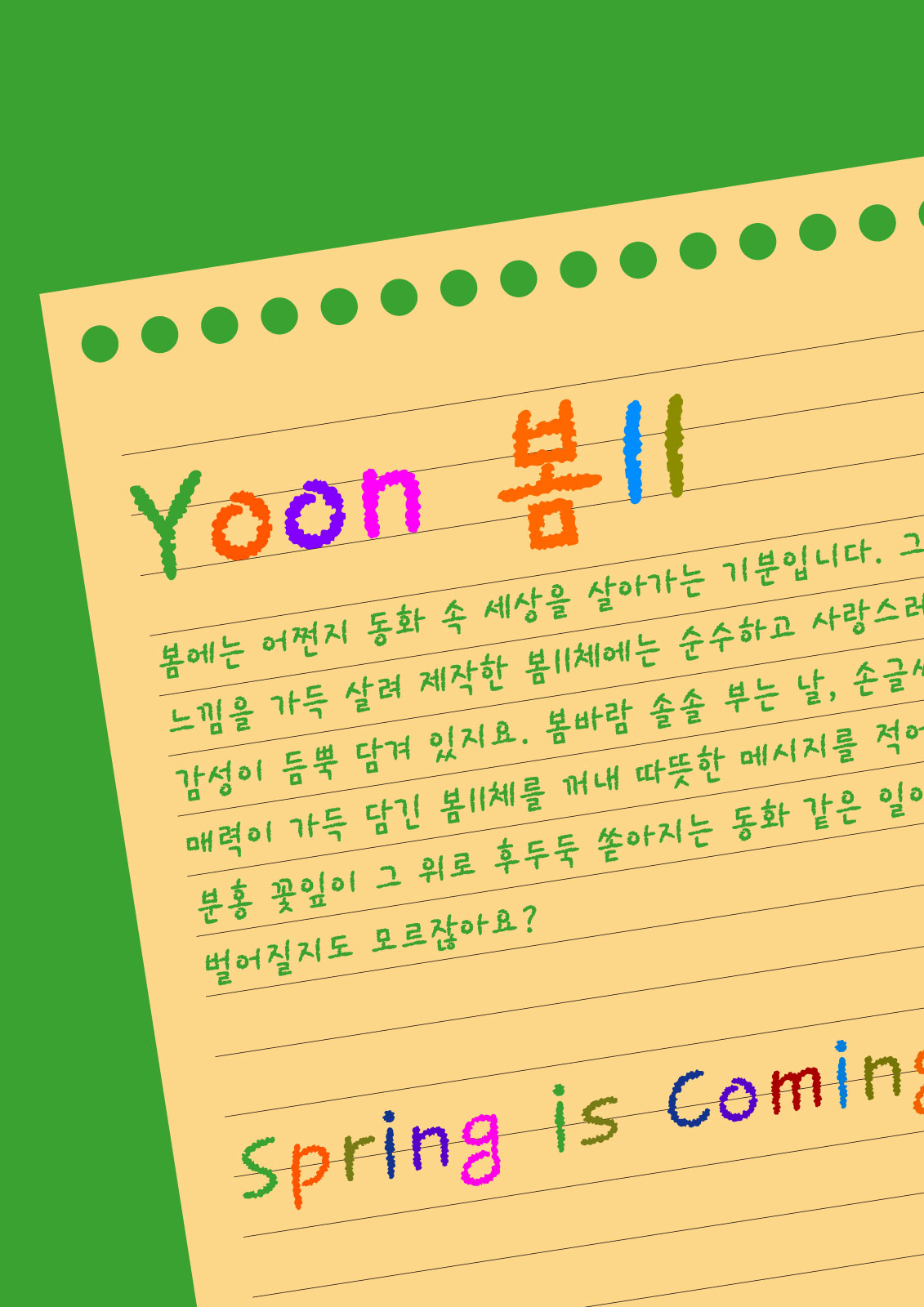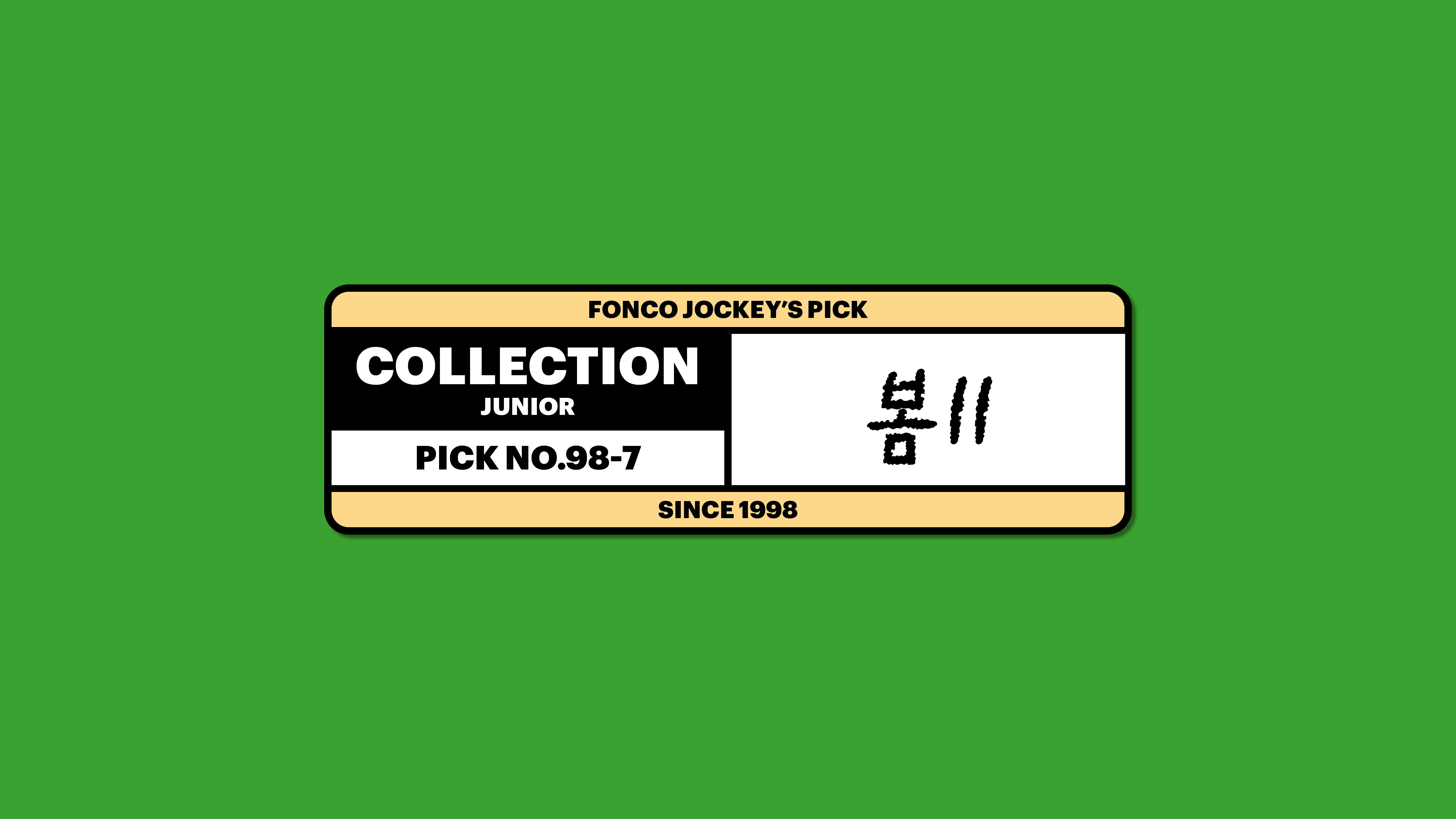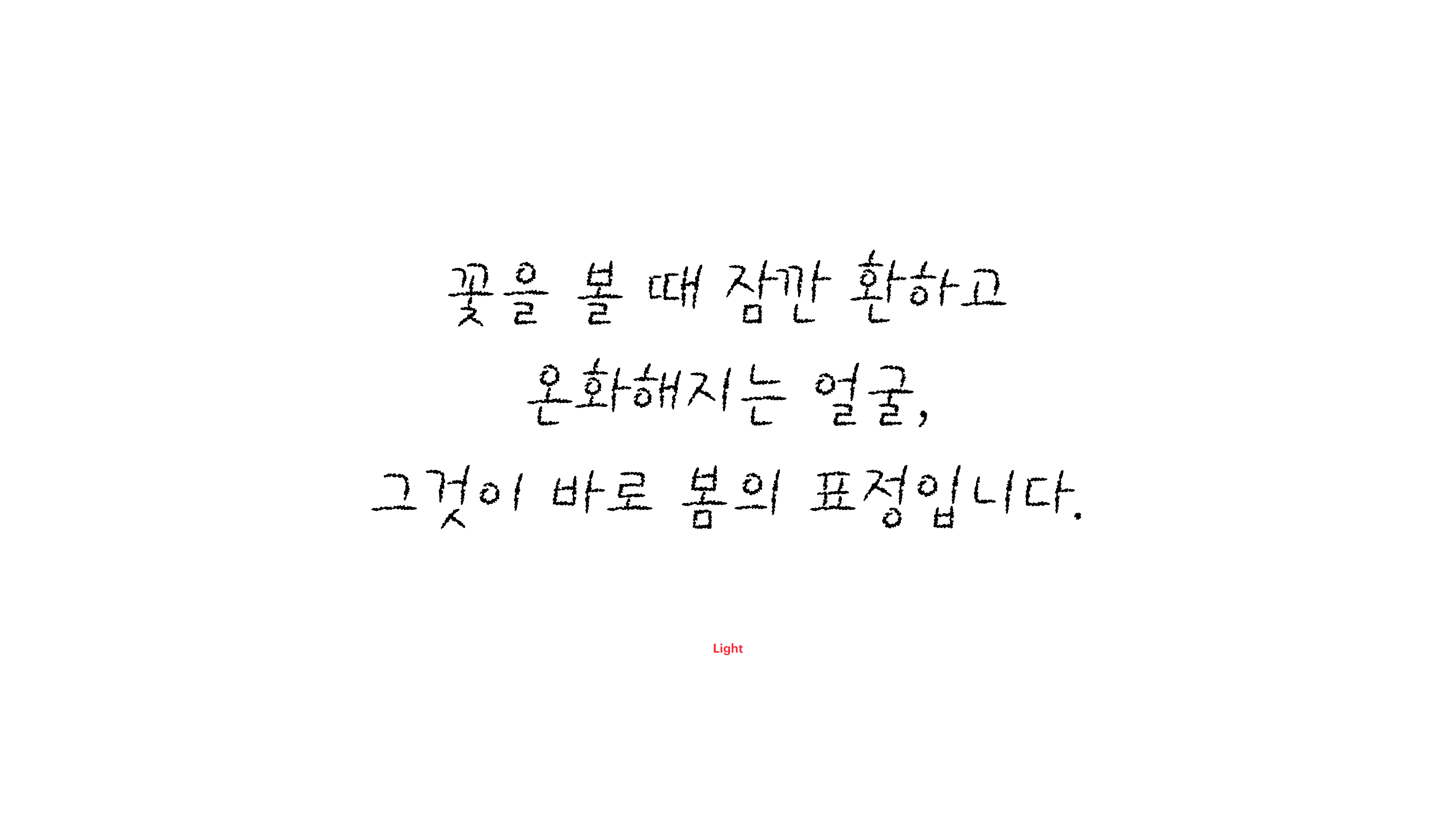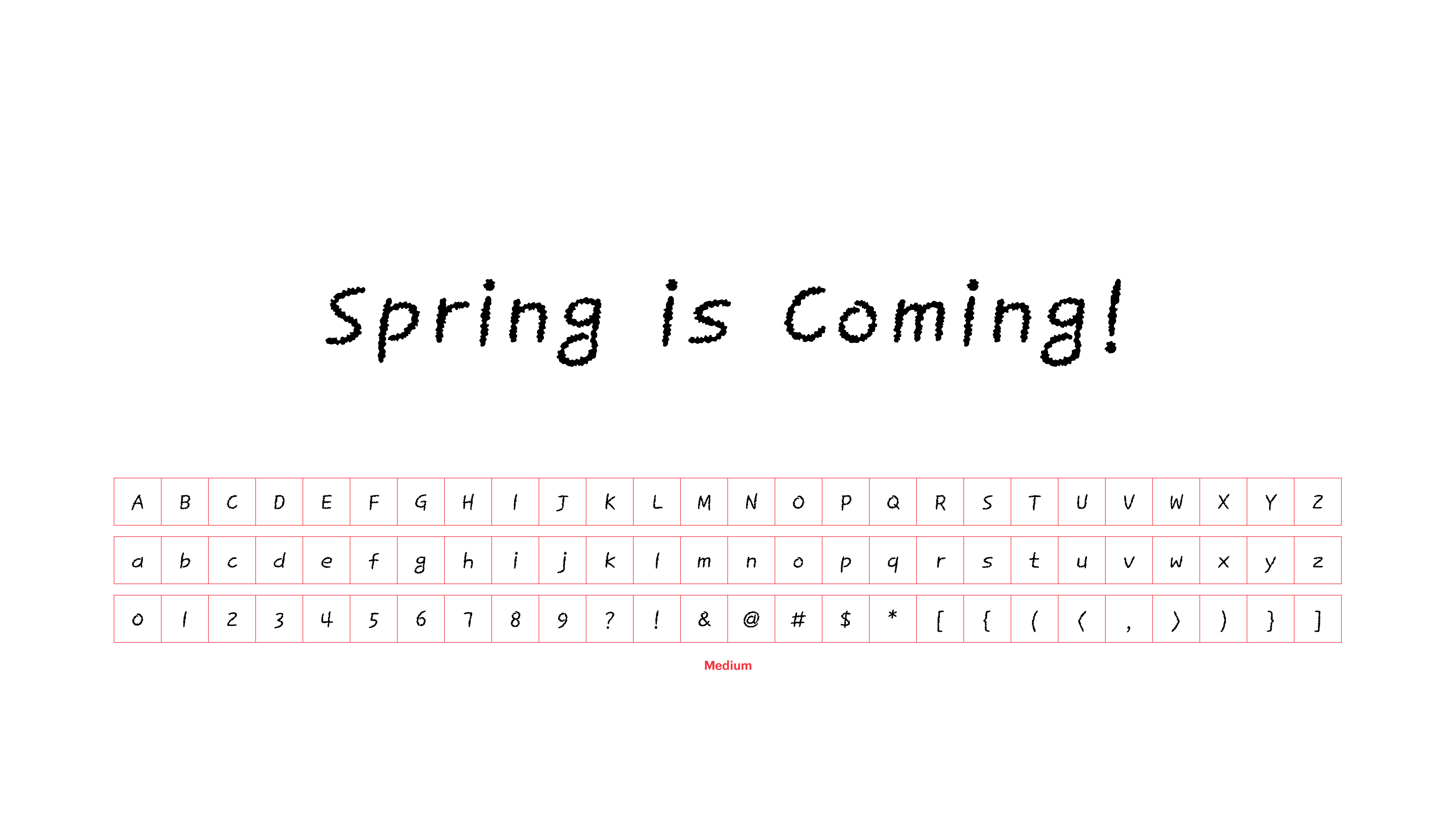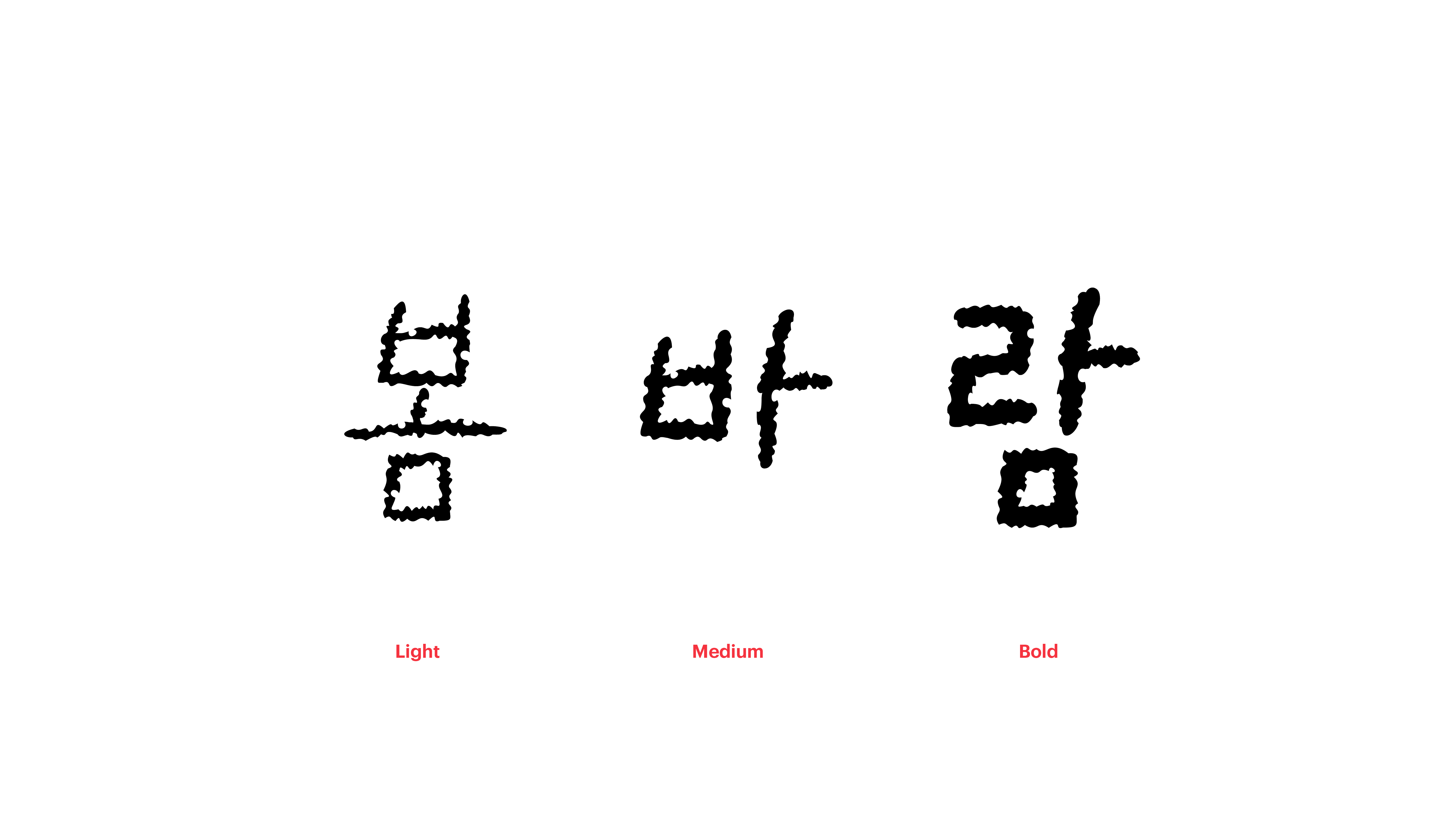
봄II
Yoon 봄II
봄에는 어쩐지 동화 속 세상을 살아가는 기분입니다. 그런 느낌을 가득 살려 제작한 봄II체에는 순수하고 사랑스러운 감성이 듬뿍 담겨 있지요. 봄바람 솔솔 부는 날, 손글씨의 매력이 가득 담긴 봄II체를 꺼내 따뜻한 메시지를 적어보세요. 분홍 꽃잎이 그 위로 후두둑 쏟아지는 동화 같은 일이 벌어질지도 모르잖아요?